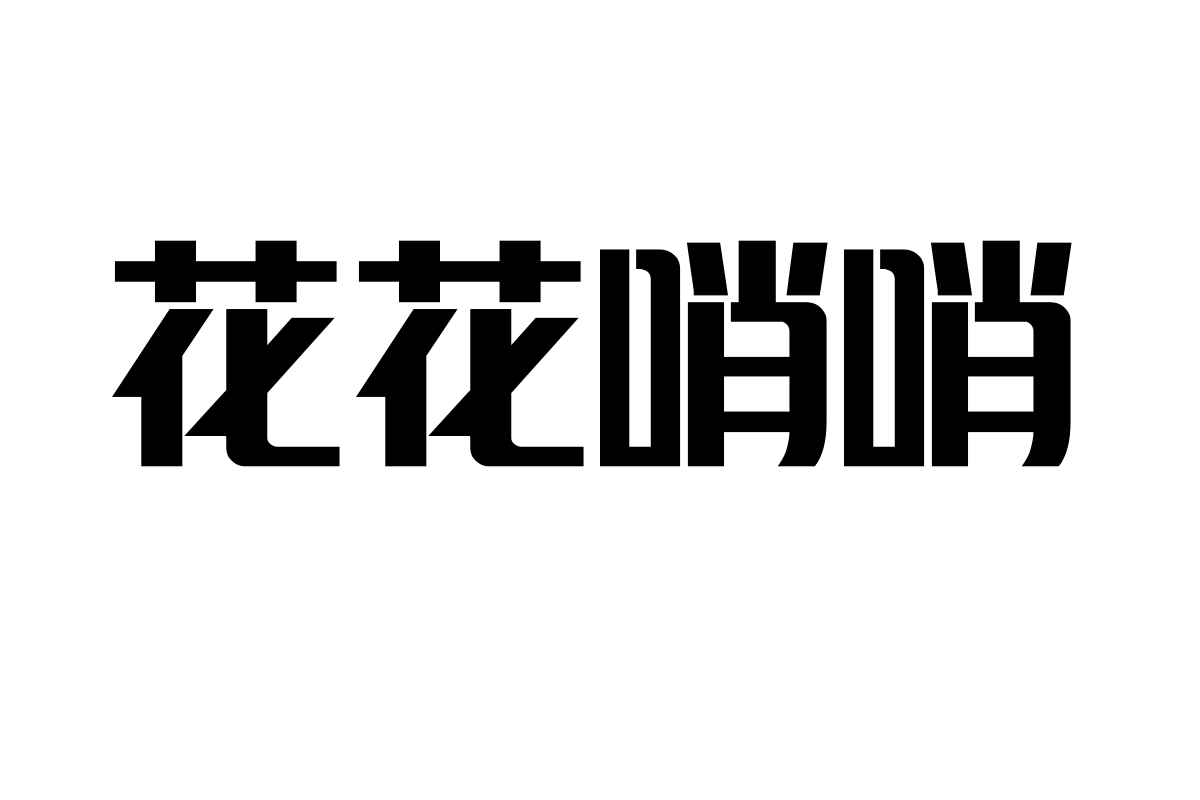
上首锐圆体是一款具有独特风格的中文字体,由上海字库科技有限公司设计。这款字体采用了锐角和圆润相结合的设计,使得字形更加饱满、富有层次感。同时,字体结构紧凑,笔画流畅,整体给人一种简洁明快的感觉。
上首锐圆体适用于各种需要展示中文字体美感的场景,如广告设计、海报制作、网页设计等。它的出现为设计师们提供了更多的选择,使得作品更具个性和创意。